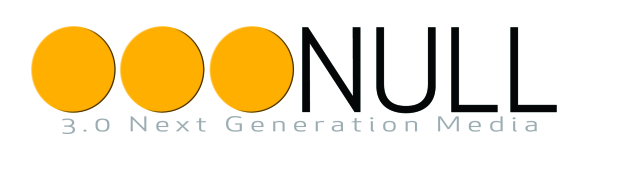
Welche Schrift passt bei diesem Logo?
einige Stundenten und ich nehmen gerade an einem Projekt teil: Wir produzieren eine Medienzeitschrift der Zukunft. Hierfür habe ich ein Logo entworfen, bin aber mit meiner Wahl der Schrift(en) noch nicht ganz glücklich.
Die Zeitschrift soll "3 Punkt Null" heißen. Das Logo bzw. die Schrift soll Bewegung vermitteln, "in die Zukunft steuern" und möglichst breit laufen. Die Zeitschrift soll nicht nur Themen die jetzt aktuell sind behandeln sondern auch in die Zukunft schauen. Das Logo soll diese Idee auch mit den gewählten Schriften vermitteln. Was könnte denn da am besten passen? Ich hoffe, man kann mit meiner Beschreibung etwas anfangen ;-)
ich würde eine "rundere Schrift" nutzen - in keinem Fall eine eckige!
Allerdings darf die Schrift auch nicht zu fett sein...
Schau Dir mal die Futura-Family an... oder etwas ähnliches...
P.s. noch eine Frage: Du spricht von Bewegung - wo würdest Du die denn hinein interpretieren?
ein paar anmerkungen:
– die klassische schriftwahl, wenn bewegung ausgedrückt werden soll, ist die kursive. die rennt ja schon dem namen nach. natürlich ist das abgelutscht, aber es funktioniert.
– wenn ihr eine breit laufende schrift wollt, dann nehmt eine breit laufende schrift. zerrt keine normale in die breite, wie in dem gezeigten logo. wenn mich meine entzündeten augen nicht trügen, handelt es sich um eine misshandelte apex new. mir tut sie ein wenig leid.
– habt ihr schon mal über … nachgedacht? wenn man sich drei punkt null nennt, drängen sich die auslassungspunkte als logoelement förmlich auf. sie verweisen auf die (ungewisse) zukunft, in der das ausgelassene vielleicht durch irgendjemanden ergänzt wird.
Also an Hand der Beschreibung würde ich gleich sagen: Der Kleine hat noch Flausen im Kopf! Dynamik, Zukunft ... wo gibt es das den noch? ;-)
Nach einem Blick auf das Logo sehe ich auch keine Notwendigkeit für eine Windschiefe. Das 3.0 drängt bei mir die Asoziation zu Fixweiteschriften wie Letter Gothic in den Kopf. Besonders für die Untere Zeile wäre das in Betracht zu ziehen. Für das Wort ,,NULL'' bietet sich IMHO als breit laufende Schrift eine Microgramma/Eurostyle an. Eine Windschiefe würde IMHO irgendwie nicht zu den Kreisen passen. Falsche Richtung der Orientierung im Raum ...
Mein Vorschlag zur Lösung: Logo genau so lassen, NULL mit einer Eurostyle Black und die Zeile darunter in einer Letter Gothic (oder einer ausgefransten Variante wie DaisyWheel) setzen. Vielleicht ist dieser antiästhetische Neobrutalismus ja passend? :hammer: